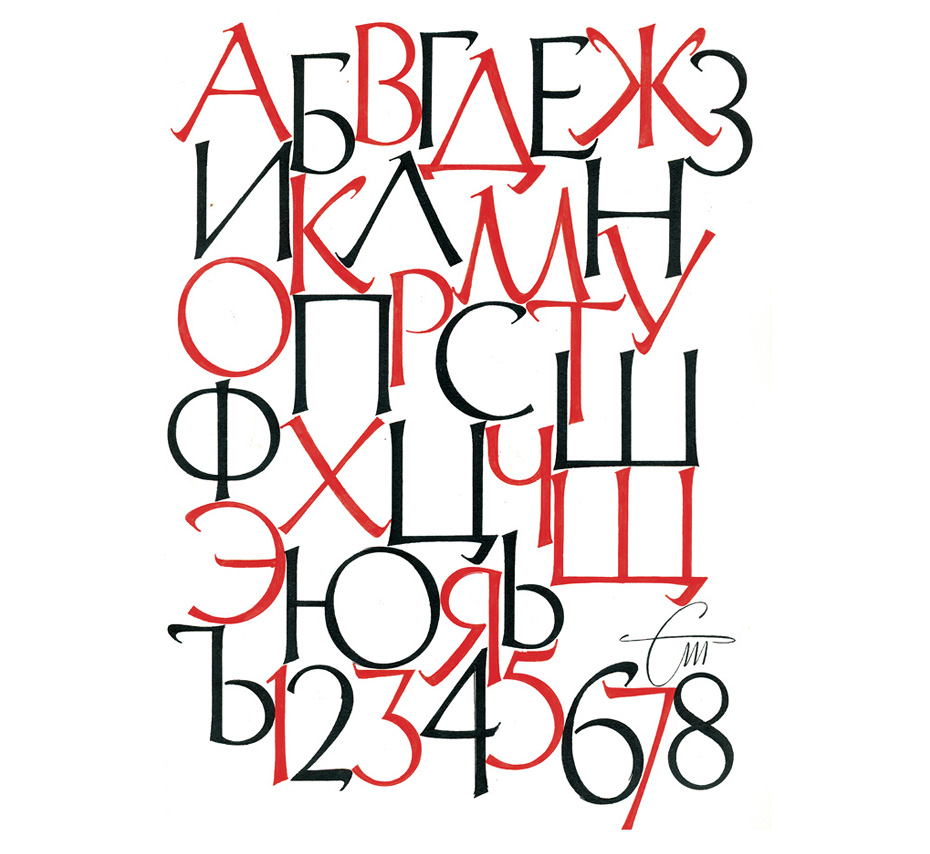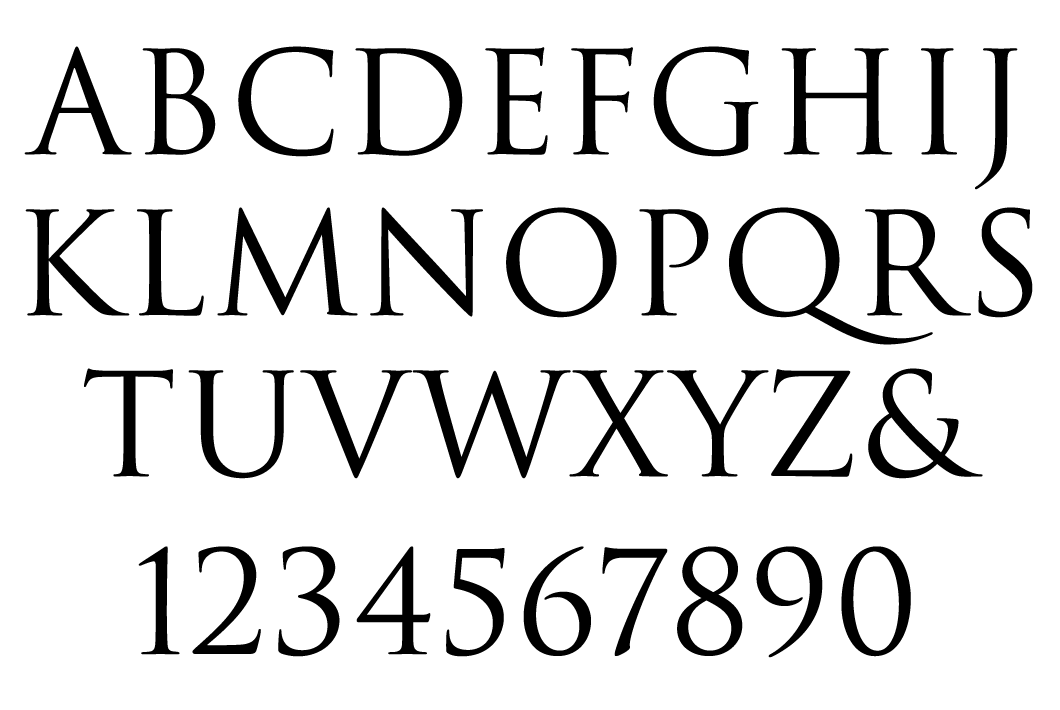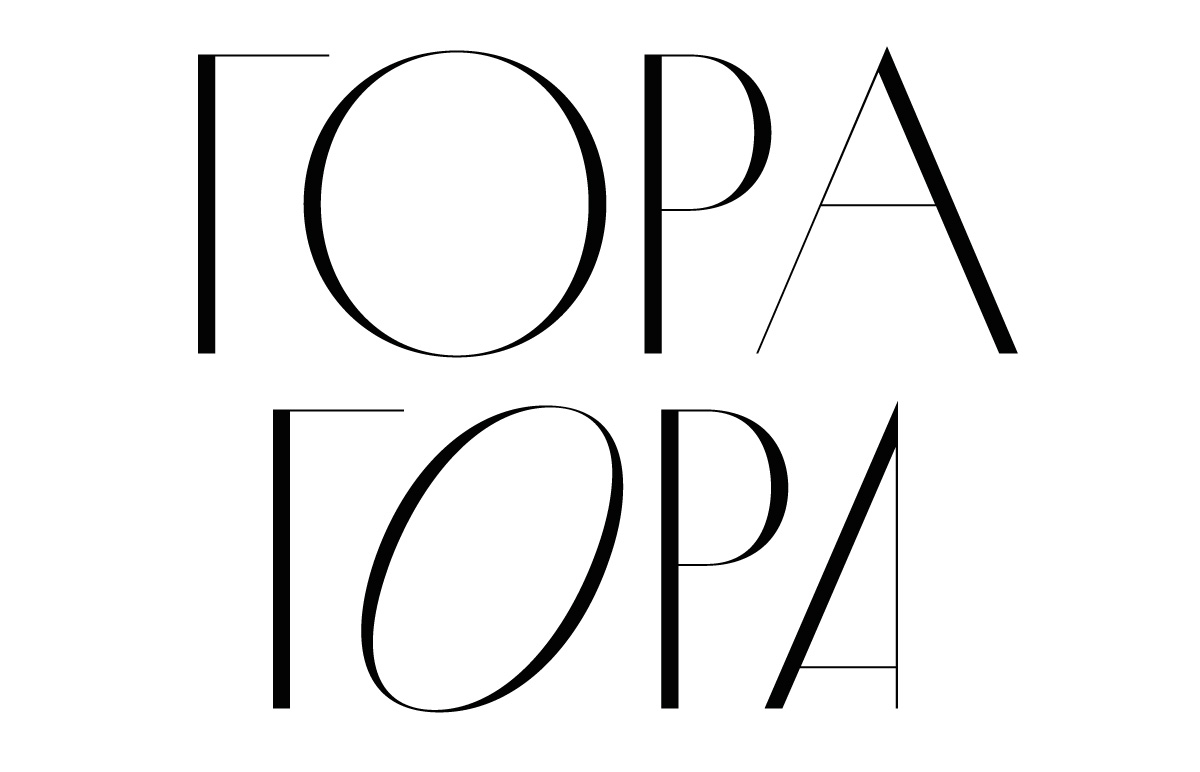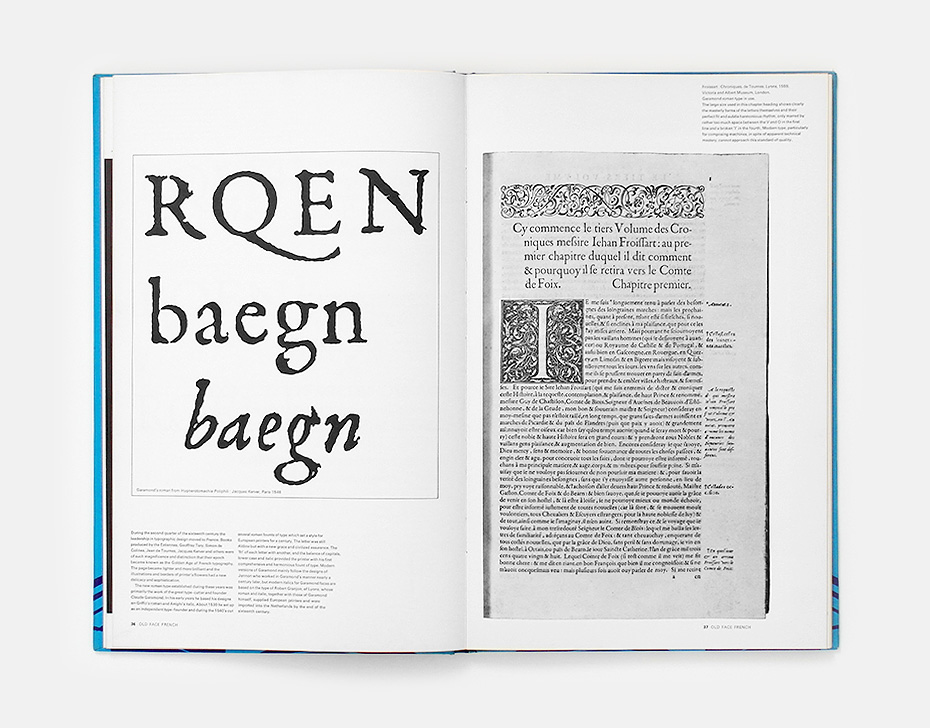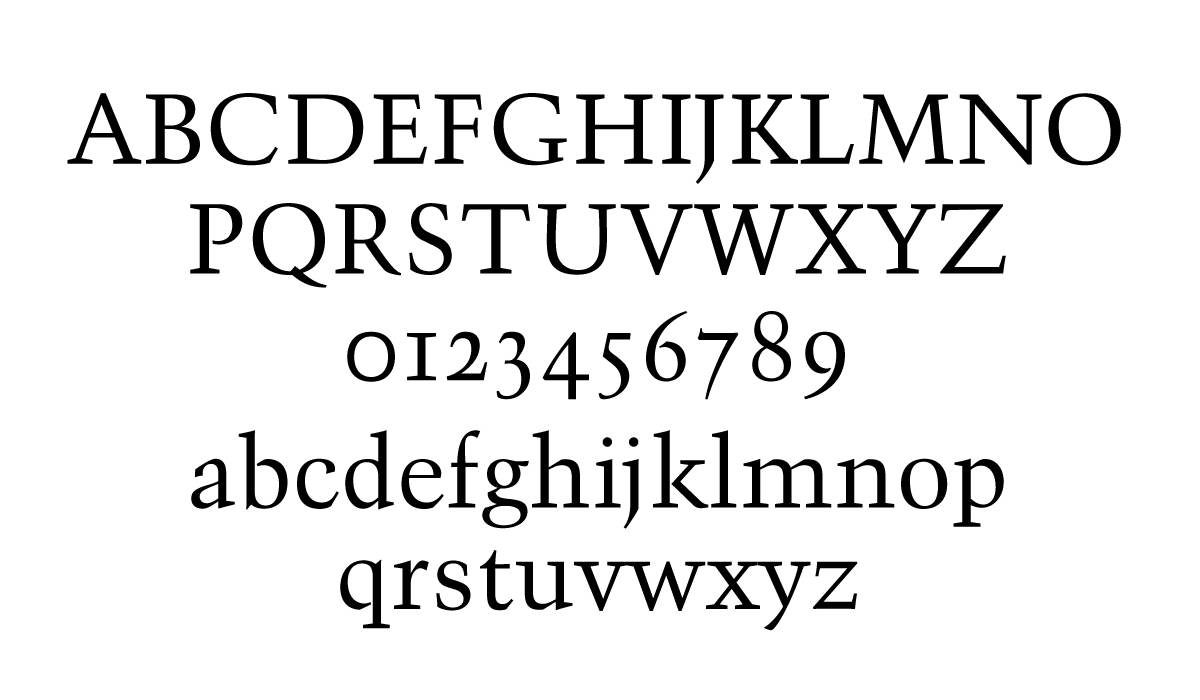
Рустам Габбасов: «Шрифт – это искусство!»
Оказавшись в арт-резиденции Переделкино в буквальном смысле слова за одним столом с Рустамом Габбасовым, сооснователем специализированного онлайнового журнала «Шрифт» и сопутствующего ему издательства Sсhrift Publishers, я не мог упустить возможность поговорить с ним о его любимом деле.
Потому что шрифтовики – совершенно отдельные люди, вызывающие восхищение у и филологов, и у дизайнеров: то, чем они занимаются, ускользает от рационального понимания – но хорошо чувствуется на подсознательном уровне.
Мой первый вопрос – о том, когда и почему возникло это издательство, столь узко специализированное?
Рустам Габбасов: Оно возникло осенью 2013 года по очень простой причине. Мне и моему другу и соиздателю Евгению Юкечеву очень не хватало ресурса, на котором бы регулярно появлялись профессиональные тексты об истории шрифта, о типографике, о книжном дизайне. Мы оба были в тот момент выпускниками Британской школы дизайна, отучились на курсе у Ильи Рудермана, основателя шрифтовой студии CSTM Fonts (совместно с Юрием Остроменцким) и шрифтового магазина type.today. И вот в 2013 году мы запустили онлайн-журнал под названием «Шрифт» (typejournal.
ru), пригласили к участию редколлегию. Нам очень важно было, чтобы у нас был экспертный состав коллег, с которыми мы могли бы сверять наши планы.
С кем же?
Рустам Габбасов: Юрий Гордон, Валерий Голыженков, Дима Барбанель, Евгений Григорьев, Гаянэ Багдасарян, Владимир Кричевский, Илья Рудерман и Эмиль Якупов. Это был замечательный профессиональный состав редколлегии. Мы задумали сайт не как какой-то бодрый медиаресурс, где каждый день что-то будет появляться. Скорее как ресурс, который говорит неспешным языком с внимательным читателем. Тем читателем, который хочет читать лонгриды, очень качественно проиллюстрированные, чистые с точки зрения прав. Это принципиальный момент. Тогда (да и сейчас) шрифтовой рынок сильно страдал от пиратства, и нам хотелось обратить внимание читателей на правовые вопросы.
Прежде чем мы перейдём к истории со шрифтами, ещё пару слов об истории с вашим сайтом.
Я так понимаю, это история абсолютно некоммерческая. Вы не ставили себе цели зарабатывать…
Рустам Габбасов: Зарабатывать – нет, конечно.
А как же?
Рустам Габбасов: У проекта несколько учредителей, вернее, партнёров. Все они оказали финансовую либо техническую помощь. Во-первых, в 2013 году это была компания «Яндекс», которая с энтузиазмом идею такого журнала восприняла. Дима Барбанель вместе с «Яндексом» создавал тогда Сampus, регулярные интенсивы для дизайнеров в Подмосковье. Женя при поддержке Мастерской Димы Барбанеля представил проект журнала «Яндексу». Так у нас появился хороший бюджет, который нам позволил запуститься.
То есть вам просто выделили бюджет. А по какому департаменту его провели? По пиару, по разработкам?
Рустам Габбасов: Нет, по коммуникациям, если не ошибаюсь. Департамент дизайна тогда в «Яндексе» возглавляла Лола Кристаллинская.
Бюджет позволял нам поддерживать финансово наших авторов, наследников художников — мы старались держать планку гонораров на достойном уровне и даже гордились этим.
Да уж, действительно, повод для законной гордости!
Рустам Габбасов: Для нас это была принципиальная установка. Ещё одним партнёром была компания «ПараТайп», которая и сегодня нас поддерживает – это известнейшая в России студия, выпускающая шрифты с кириллицей, и лично Эмиль Якупов – на тот момент директор компании. Его энергия и блестящая эрудиция нам помогли найти опорные точки в работе. Так с финансовой и дружеской помощью партнёров мы и запустились – с негласным условием, что никто не вмешиваeтся в редакционную политику. Мы, естественно, не должны были как-то подспудно рекламировать ни «Яндекс», ни «ПараТайп» – это была меценатская, просветительская история с их стороны.
И как же вы перешли от издания сайта на деньги просвещённых спонсоров к изданию книг? Конечно, история естественная, что люди, озабоченные шрифтами, хотят видеть свои шрифты на бумаге.
Но как это практически осуществилось?
Рустам Габбасов: В 2013 году прошла первая международная шрифтовая конференция «Серебро набора»…
Какое название!
Рустам Габбасов: «Серебро набора» – это несколько снобистский термин, которым типографы-классики называют идеально ровный блок текста, однородный по цвету отпечатка набор: красивый, чёткий, без просветов и дырок. По одной из версий, он возник в эпоху голландских издателей Эльзевиров, их безупречно набранные и отпечатанные книги восхищали современников. И к этой конференции (а мы там рассказывали про журнал) нам хотелось что-то выпустить, что можно подарить, продать, показать. Это была небольшая брошюра, которую мы подготовили на основе нашей первой публикации в журнале. Она называлась «Гражданский шрифт и кириллический Киш».
КиШ?!
Рустам Габбасов: Киш. Сейчас поясню. Автором этого очерка был Владимир Венедиктович Ефимов – художник, график, арт-директор компании «ПараТайп».
Это его рассказ о том, как он cпроектировал кириллический состав знаков в гарнитуре, которая называется Kиш (Kis) – по имени художника и пуансониста Николая Киша (Tótfalusi Kis Miklós, 1650–1702). Он венгр по происхождению, уникальнейшая личность – не будучи ни художником, ни гравёром, а будучи, в общем, человеком слова, философом и теологом, он оказался откомандирован в Амстердам для того, чтобы изучить ремесло типографа и шрифтовика и на венгерском языке издать Библию. Он отправился в Амстердам и не только научился у голландцев ремеслу типографа и издателя – он их во многом превзошёл. И оставил после себя приличное количество шрифтов, образцы которых сохранились во многих европейских странах. И вот антикву Kis, которая в цифровом виде уже существовала в компании Bitstream, Владимир Ефимов и кириллизовал. Это был интереснейший процесс, где он рассказывает ещё и очень кратко об истории гражданского шрифта.
У него была идея, что если бы Пётр не торопился, а посмотрел вокруг и обратился к каким-то ярким образцам антиквы того времени, то кириллица послереформенная могла бы выглядеть немножко иначе.
А одним из лучших образцов как раз были шрифты Николая Киша. Мало того, у Петра на уровне двух рукопожатий был доступ к этому человеку – просто не сложилось. Русские послы знали о Николаусе Кише, и если бы Пётр с ним познакомился, это был бы несколько иной дизайн-процесс, говоря современным языком.
Но ведь венгерский алфавит пишется латиницей. Там есть всякая диакритика, но на основе латиницы. А были к тому времени гражданские, не церковные кириллические шрифты – в Болгарии, в Сербии? Или Пётр был первым, кто заказал светским шрифтовикам кириллицу?
Рустам Габбасов: Пётр был первым, кто, что называется, примерил гражданское платье на полуустав. Он очень хотел латинизировать саму графику. И, конечно, это был абсолютно прорывной проект. Можно вспомнить разве что Людовика XIV. У него был похожий проект. Он не занимался, естественно, изменением графики алфавита, но он создал, по сути, государственный шрифт – так называемую королевскую антикву.
Это был очень серьёзный проект с комиссией из художников и гравёров, которые спроектировали romaine de roi, королевскую антикву, ей набирались самые торжественные и важные документы, книги в том числe, например, сборник, посвящённый всем наградам и медалям эпохи Людовика.
Я понимаю, что вы сели на своего конька. Но давайте вернемся от Людовика к вам. Итак, вы выпустили эту брошюру к конференции и поняли, что это хорошо.
Рустам Габбасов: И мы поняли, что наш журнал, на котором уже появилось какое-то количество публикаций, – это хороший источник для новых книг. И с 2014 года параллельно запустили издательство. Изначально мы думали, что это будет коллекционная история: брошюры, которые люди будут собирать, подшивать. Но от этой идеи мы быстро ушли.
И к чему же пришли?
Рустам Габбасов: Мы пришли к тому, что нам интересно делать хорошие большие монографии, ресурсом для которых могут быть частные архивы, коллекционеры и те исследования, которые мы параллельно готовим для журнала.
И, конечно, переводные книжки, потому что всё-таки западный типографический мир немыслим без большого количества очень качественных и хороших, интересных книг по шрифтам, чего у нас, в общем, почти и не было в тот момент.
Сколько вы книг выпускаете в год?
Рустам Габбасов: Если мы две книги в год издаём, мы считаем, что это хороший результат.
А вот когда вы говорите «мы», какое количество работающих людей имеется в виду?
Рустам Габбасов: В редакции восемь человек. Я работаю выпускающим редактором, Женя Юкечев — наш главред, я в Москве, Женя живёт в Берлине с семьёй. С нами также Олеся Гиевская, наш редактор и друг всех авторов, сейчас она живёт и работает на Кипре. Наташа Гареева — литературный редактор и корректор, Настя Минасова, исследователь, а также Владимир Пушкарёв, Науэль Бенку, Светлана Виноградова.
Последних трёх мы пригласили в редакцию в качестве интернов около года назад, и сейчас они они нам помогают с развитием соцсетей, вёрсткой новых статей в журнале, фотосъёмкой, редактурой… Вот такая разбросанная по миру, но дружная редакция, у всех есть другая работа, а «Шрифт» — это проект, которому каждый из нас посвящает свободное время по мере сил и вдохновения.
Но в экономическом или хотя бы символическом смысле оно себя оправдывает?
Рустам Габбасов: В этом году у нас есть цель — заново переделать наш интернет-магазин (им занимается как раз Володя Пушкарёв), скорректировать ритм постов в соцсетях и рассылку, проверить — позволит ли он окупать затраты на вышедшие книги, а ещё лучше — собирать бюджет на новые издания. Это будет хорошим результатом в нынешнее время.
У вас очень узкая целевая аудитория, но она очень лояльная.
Рустам Габбасов: Очень! Про нашу аудиторию хочется петь какие-то арии, петь ей дифирамбы.
Потому что это самые терпеливые люди в мире. После того, как «Яндекс» нас покинул, мы стали издавать книги по модели краудфандинга на сайте planeta.ru. Вот эти две условные книжки в год – это, как правило, краудфандинг.
То есть вы сначала собираете заказы…
Рустам Габбасов: Пока мы делаем книжку, идут предзаказы, и после того, как книжка из типографии приезжает, мы треть тиража сразу рассылаем…
А какие у вас тиражи?
Рустам Габбасов: 500 и 1000. Последние книжки мы тысячным тиражом делали, и этого нам хватает, чтобы ещё понемногу остаток тиража распродавать. Так вот, читатели, которые участвуют в краудфандинге, готовы ждать эту книгу иногда больше, чем полгода после того, как мы получили тираж, потому что нам нужно ещё спланировать рассылку, собрать «акции», которые есть всегда в краудфандинге. В общем, это всегда технически непростая история, и мы, несмотря на все наши промахи, откровенные косяки и недоработки, практически никогда не получали от наших подписчиков каких-то нареканий.
Ну а тиражи-то эти расходятся?
Рустам Габбасов: Расходятся, но небыстро. Некоторые быстрее. У нас есть такой термин внутри издательства – «фестивальные книги». Это книги, про которые мы заранее знаем, что они будут хорошо расходиться. Такой книжкой был наш «Путеводитель по кириллице», в котором мы собрали все наши рейтинговые публикации. Мы каждый год в журнале публикуем что-то вроде топа «10 самых интересных шрифтов с кириллицей». Эти публикации популярны – мы по статистике посещений видим. Всё-таки люди любят рейтинги, хотя эти публикации не про раздачу медалей — они скорее про экспертный, любопытствующий взгляд на прошедший шрифтовой год. В результате после пяти лет публикаций таких рейтингов мы собрали из них книгу. То есть одновременно это великолепные образцы шрифтов на бумаге – можно держать книгу на полочке, можно посмотреть на них, шрифты свёрстаны в разных ситуациях типографических – от суперкрупного кегля до очень мелкого. И плюс мы добавили в эту книгу (чтобы это не был просто альбом шрифтов), два хороших исследования. Одно из них написал Евгений Юкечев – это краткий экскурс в историю кириллицы, от самых первых её этапов появления и развития через все кульбиты к современности. И второе исследование написали наши друзья, каллиграфы, дизайнеры Ира Смирнова и Макс Ильинов. Оно скорее философское и посвящено тому, какие сейчас есть пути развития кириллической графики: чем могут люди вдохновляться, где спрятаны источники вдохновения.
Евгений Юкечев 2021 Фото: Екатерина Чащина/ журнал «Шрифт»
Как раз по поводу путей развития шрифтовой графики хотел у вас спросить: пришествие компьютеров, которые стали персональными, но при этом унифицированы – у всех или семейство вшитых предустановленных шрифтов виндоусовских, или, соответственно, эппловских – это облегчает задачу дизайнера-типографа – у всех всё одинаково! – или, наоборот, усложняет ее?
Рустам Габбасов: Если честно, то для профессионального типографа это не так уж важно – то, что сейчас у всех пользователей на всех компьютерах одни и те же шрифты установлены. Потому что всё-таки профессиональный типограф обращается не столько к простым юзерам, которые используют Microsoft Word для набора своих текстов, а всё-таки к коллегам-дизайнерам. А коллеги-то прекрасно знают, что шрифтовой мир гораздо шире, чем те стандартные шрифты, которые установлены в компьютер. И в этом смысле компьютерный шрифтовой дизайн, конечно, открыл огромные возможности для графиков. Это был прорыв – стало возможно у себя дома, за рабочим столом, не просто рисовать, проектировать новые шрифты, но и тут же ими пользоваться, не обращаясь ни в типографии, ни в сторонние печатные дома. Исчезла морока с плёнками, которые нужно выводить, проверять и прочее, прочее. Всё очень ускорилось, произошло даже перенасыщение новыми шрифтами. Но у нас, в отличие от Запада, ситуация немного иная – у нас до этого перенасыщения пока ещё далеко. Как только появляется какой-то новый оригинальный качественный шрифт с кириллицей, профессиональное сообщество дизайнеров мгновенно вбирает его в себя, осваивает, он появляется на улицах, в книжках, в журналах и так далее.
Это вы так деликатно говорите о нелицензионном использовании?
Рустам Габбасов: Нет. В том-то и дело, что сейчас всё больше и больше шрифты используются легально. В этом смысле рынок шрифтовой немного подправился. Ушла та эпоха, когда шрифты продавались на дисках на Горбушке. Сейчас пользователи относятся к шрифту как к вещи коллекционной, как к вещи, которая у тебя будет храниться долго на компьютере (имеется в виду лицензия), и ты сможешь пользоваться ей снова и снова, то есть как к некому вложению средств.
А есть ли вообще при разработке новых шрифтов какая-то мера? Когда модификация известного шрифта становится новым самостоятельным шрифтом? Если я добавлю к засечкам с каждой стороны по два пикселя, это будет новый шрифт? Как вообще это определяется?
Рустам Габбасов: Конечно, можно взять какой-то готовый шрифт и чуть-чуть что-то в нём поменять, и это даже может не стать прецедентом в суде. Но это бессмысленная работа. Поиск нового образа в шрифте абсолютно такой же, как поиск нового образа в живописи, в литературном произведении – в любой творческой работе, потому что шрифт – это искусство.
Там есть свои законы, по которым ты добиваешься, доползаешь до нового ощущения от шрифта. У шрифтов, которые, казалось бы, даже очень похожи на уже существующие, есть невероятное влияние на читателя. Оно достигается за счёт изменения параметров не столько микротипографических – не в засечках дело, — а макротипографических, например, в отношении высоты строчного знака к высоте прописного, в изменении контраста внутри знаков, то есть перепаде толщин – как самый тонкий штрих относится к самому толстому. От таких нюансов меняется динамика чтения, восприятие текста.
Вот на таком макроуровне профессиональный шрифтовой дизайнер и работает – как диджей, передвигающий ручки на микшере. Он взаимодействует с существующими историческими стилями и эпохами, но, чтобы сделать шрифт новым и современным, чуть меняет эти настройки. Так появляются новые оригинальные шрифты. Сегодня есть большие возможности технологические, связанные с программированием, не только с рисованием. Ведь шрифтовое семейство можно задумать как гарнитуру из двух шрифтов – прямое и наклонное, например, а можно – из сорока: ты нарисовал самое светлое, самое жирное, а остальное за тебя делает компьютер, интерполирует все градации, и ты из них можешь выбрать то, что тебе нужно. Такое подключение к творческому технологического процесса – это тоже интересно.
Включаются ли в современные гарнитуры эмотиконы? Или, проще сказать, эмоджи? Потому что людям, которым сейчас меньше 20 лет, уже неудобно переписываться без эмотиконов. Это стало частью стандартной переписки.
Рустам Габбасов: Эмотиконы встроены в операционные системы, и ты быстро к ним можешь добраться. А шрифт подключить, например, в тот же айфон и заменить им те эмотиконы, которые там есть, это уже непросто. Но есть, во-первых, очень давняя традиция шрифтов из неалфавитных знаков. Например, шрифтов, в которых есть только знаки зодиака или фазы луны. Это очень давняя традиция, которая идёт ещё из эпохи металлического набора, и сегодня дизайнеры, рисуя даже текстовый шрифт, всегда добавляют туда огромное количество символьных элементов – стрелки или «персты указующие».
Дизайнеры любят отрываться именно на этих элементах – там можно порисовать эти руки, они смешные.
«Персты указующие» – это здорово, но я говорю о детях, которые сейчас растут на смартфонах, где эти самые эмотиконы, эмоджи встроены уже в обычный текст. Им дальше уже некомфортно будет без этих рожиц в обычной своей взрослой и профессиональной жизни общаться. Вы это предвидите как-то?
Рустам Габбасов: Я всё-таки не верю, что возможно обойтись, во-первых, без начертания рукой всех алфавитных знаков, без письма, и, во-вторых, без шрифта, где есть знаки, которые можно читать. Ведь это явления, которые буквально сидят в нашем ДНК.
В нашем, но не наших детей.
Рустам Габбасов: Там просто произойдут какие-то гибридные процессы. Потому что на одних только эмодзи невозможно научиться читать. Понятное дело, что будут, и уже есть книжки, где история рассказана только какими-то эмодзи, но все нейронные связи у нас отомрут, если мы лишимся привычного алфавита. Невозможно научиться мыслить, не записывая что-то рукой сначала, а потом не взаимодействуя с печатным текстом.
Тогда позвольте вам предложить еще более глобальный вопрос. Есть западноевропейский алфавит, который одинаков от Швеции до Италии. Да, есть диакритика, какие-то дополнительные значки, но любое слово шведского языка можно узнаваемо записать на итальянской пишущей машинке, и наоборот. Есть языки и алфавиты, заведомо ничего общего не имеющие с западноевропейским: грузинский, армянский. Это совершенно отдельные знаковые системы. А наша с вами родная кириллица как бы занимает промежуточное положение – вроде как большинство знаков у нее совпадает с европейскими, но в слова эти знаки, с точки зрения европейца, всё-таки не складываются.
Рустам Габбасов: Да, можно так сказать.
Вы, кириллические шрифтовые дизайнеры, в европейском семействе шрифтовиков кем себя чувствуете? Бедными родственниками или, наоборот, обладателями суперспосбности – вы и так, и эдак можете?
Рустам Габбасов: Нет, такой суперспособности, к сожалению, нету. Но по поводу ощущения «бедных родственников» по сравнению с латиницей – это очень интересный разговор. С момента перестройки, когда в стране появились первые компьютеры, стали появляться первые шрифты с кириллицей, часто у кириллических дизайнеров было снобистское отношение к западным шрифтовым дизайнерам – мол, они никогда не смогут нарисовать качественную кириллицу.
Оно им надо?!
Рустам Габбасов: Оно им нужно было, потому что, когда появились компьютеры с «Виндоус», мы получили огромное количество системных шрифтов с некачественной кириллицей. Люди, их рисующие, просто не воспринимали кириллицу как какой-то алфавит, которому нужно уделить внимание. Допустим, сотню языков поддерживает шрифт Times New Roman, и кириллица – просто ещё один алфавит, зачем же к нему как-то особенно относиться?
Сотня языков – это не сотня алфавитов. Едва ли Times New Roman поддерживает сотню алфавитов.
Рустам Габбасов: Он поддерживает, конечно же, не сотню алфавитов, но всё-таки к проекту приглашались серьёзные консультанты, которые, во-первых, владеют тем или иным языком и знают, как выглядит графика их алфавита. А с кириллицей такого не происходило. Мы получили ужасный шрифт Arial, который сам по себе отличнейший проект в латинице, но в кириллице он просто-напросто страшный. И у нас он был повсеместно на всех вывесках.
Но за последние годы произошла благостная глобализация, я бы сказал. Западные шрифтовые дизайнеры без стеснения обращаются к молодым ребятам у нас в России, которые рисуют шрифты, за консультацией. Это отдельный жанр работы шрифтового дизайнера кириллического, – консультации, потому что это особое умение – объяснить коллеге с Запада, где что-то неправильно нарисовал или нарисовал правильно, но ошибся с пропорцией буквально на пару пунктов – и в строке это сразу видно.
И эта история сейчас продолжается. Люди, которые самостоятельно рисуют кириллицу на Западе, стали делать гораздо меньше ошибок. И, например, в пакете шрифтов от компании Adobe уже есть гарнитуры, которые нарисованы без привлечения наших дизайнеров в качестве консультантов, но они выглядят очень хорошо – ими можно набрать серьёзную книжку, длинный текст. И вот это процесс, в котором мы (редакция журнала) себя видим тоже как некий катализатор, что ли. И с помощью журнала и отчасти при помощи наших книг эту довольно маргинальную идею о кириллице – «это только наше, и только мы можем это сделать», мы за последние 10 лет подразрушили. Пожалуй, мы сделали шрифты и типографику актуальной, даже модной темой – и сообщество дизайнеров, которое нас читает, видит, насколько это интересная, экспертная тема. Я рад, что мы смогли для довольно широкой аудитории рассказать о наших коллегах, о наших друзьях, о молодых дизайнерах, которые, отучившись в разных вузах, продолжают рисовать шрифты.
А общаетесь ли вы как-то более тесно с нашими, можно сказать, братьями по кириллице – болгарами, сербами, украинцами, белорусами, македонцами? Может быть, заказываете им статьи, книги?
Рустам Габбасов: Это интересная тема. У нас есть замечательные авторы, которые живут в Украине. Например, Константин Головченко – блестящий исследователь, он написал для нас несколько статей. Но статьи именно об особенностях графики украинского алфавита ещё ждут своего часа. Там есть свои особенности. В «Путеводителе по кириллице» мы их частично показали, нужно продолжать. С болгарами интересно – их кириллица похожа на нашу, но они отстаивают, например, непривычные нам выносные элементы. Или рукописные формы строчных «д», «з», «в». И у них таких микросдвигов в графике алфавита довольно много, причём она тоже не очень устоявшаяся, как и в нашем случае.
«Болгарица» рядом; а надо ли нам всем учить китайский? То есть, займёт ли иероглифическое письмо то место, которое сейчас в нашем мире занимает латинский алфавит? И что будете делать вы, шрифтовики?
Рустам Габбасов: Не думаю, что в ближайшее время это произойдет. Всё-таки это отдельная вселенная, про которую мы почти ничего не знаем и ничего не понимаем, как это устроено и с точки зрения графики, и смыслов. И поэтому, кстати, специалисты по иероглифам на вес золота.
Напоследок вернёмся от глобального к конкретному. Какие ваши ближайшие пара книг?
Рустам Габбасов: Из ближайших – та, которой занимаюсь здесь в резиденции, она называется «Modern Typography» («Современная типографика»), эссе английского типографа Робина Кинросса. Это краткая, ёмкая, и полная спорных мыслей история типографики и, самое главное, попытка разобраться, что такое понятие современности в типографике, в типографическом мире. С какого момента типографика стала себя осмыслять как самостоятельную дисциплину и искусство. И в этом году мы переиздадим нескольких наших книг. Статья Владимира Фаворского «О шрифте» выйдет в третьем издании. Эту книгу мы делаем вместе с внуком художника Иваном Дмитриевичем Шаховским. И у нас есть в планах работа над ещё одной переводной книгой, но уже с января следующего года. Эта книга называется «While we are reading» – «Как мы читаем». Автор – голландский типограф Герард Унгер, который, к сожалению, в прошлом году умер.
И у нас есть огромное количество, что называется, неизученных архивов. Архивы наследников художников, или, например, архив НИИ Полиграфмаш – в советское время была такая организация, которая занималась разработкой новых шрифтов и обслуживанием, скажем так, языков советских республик. От этого архива мало что уцелело, но то, что сохранилось (а это кальки, эскизы, это стеклянные пластинки, отчёты художников об их работе), нас очень интересуют. Мы пока не понимаем до конца, как всё это наследие превратить в книгу. Наверное, надо начать со статей, а потом уже перейти к книжке.
Новые шрифты в инстаграме: что говорит о нас наш выбор
Август стал важным месяцем для Instagram. Сначала социальная сеть выпустила довольно несуразную копию TikTok — Reels, которую сразу же встретили негативными отзывами. Еще одним нововведением стали четыре новых шрифта, которые Instagram сделал доступными для широкого использования в Stories. И вот это действительно стало событием. Да, мир переживает пандемию, вот-вот начнутся самые важные выборы в современной Америке, а в обществе царит глубокая социальная нестабильность. В этой парадигме шрифты, конечно, не самая насущная проблема, хоть как-то влияющая на нашу жизнь. Тем не менее мы решили рискнуть и проанализировать, что говорит о нас наш повседневный выбор в социальных сетях.
Мы все знаем, что выбор шрифта может многое сказать о человеке. Times New Roman и Calibri — это, как правило, соперничающие друг с другом студенческие группки на парах английского; и ничто не выдает в вас строгой чопорности больше, чем Century Gothic в качестве стандартного шрифта для электронной почты. Новые шрифты Instagram варьируются от обычных до тонких и выхолощенных, словно позаимствованных у сайта The Cut. Инстаграм не дал нам названий новых шрифтов, поэтому мы взяли смелость сделать это сами. Мы также смоделировали подходящие к ним ситуации. А потом присвоили каждому из них индивидуальность, чтобы вам было проще понять, к чему больше лежит душа. Что говорят новые шрифты о том, какой вы человек? Что подходит именно вам и вашей стратегически выверенной виртуальной личности?
Normal (стандартный шрифт) LAUREN KRANC«Я просто классная сама по себе и не задумываюсь слишком о таких мелочах»
Этот пользователь либо не подозревает, что шрифты можно менять, либо делает намеренный стилистический выбор, чтобы показать: он даже не старается и не воспринимает свои сторис в Instagram слишком серьезно. Вы похожи на тех, кто отдает предпочтение шрифту «пишущая машинка», однако более разумны. Normal — скучно, зато стабильно.
Thin Caps LAUREN KRANC«Кто еще сегодня идет на Дэйва Мэттьюза?» (южноафриканский и американский музыкант и актер. — Esquire)
Любители этого шрифта стоят прямо перед дверями метро, а не проходят к середине поезда. Они до сих пор носят свой браслет с фестиваля «Боннару» 2017 года, и у них есть уже заготовленный монолог на случай, если кто-либо сообщит, что распутавшаяся часть шнурка на браслете — рассадник бактерий. Они предпочитают янтарный эль и ведут долгие разговоры с соседями по столикам, пока их друзья не решат перестать приглашать их на ужин.
Fancy Cursive («красивый курсив») LAUREN KRANC«Розе весь день»
Любители курсива живут в очень специфическом, придуманном мире. Эти люди с легкостью могут просто не видеть всего плохого, что сейчас происходит. Они ходят на чаепития с мамой. Они делают сторис с фотоколлажами, поздравляя каждого из своих старых добрых друзей с днем рождения. Они подбирают губную помаду под цвет лака для ногтей и следят за цветовой палитрой книжных полок у себя дома.
Almost published («почти издан») JUSTIN KIRKLAND«Мир открыт ровно настолько, насколько тебе открыта книга с книжной полки, которую ты решишься прочитать»
Юзеры шрифта «почти опубликовано» (он же — шрифт «пишущая машинка») публикуют только микро- или макрофотографии. Они до смешного интроспективны. Если вам случится забрать у них телефон, вы обнаружите там целое множество неопубликованных стихотворений в заметках. Содержания? Совершенно непонятного. Такой человек предпочел бы простые, индустриальные интерьеры у себя дома, будь у него деньги, но стихи… Они просто не могут заставить себя их продать. Но когда-нибудь — обязательно. Это тот человек, который обязательно спросит на свидании, знаете ли вы что-то об А24. Ну, знаете, такая киностудия?
Bro (бро) LAUREN KRANC«Работай усердно, играй усерднее»
Использовать шрифт Bro — значит предпочитать ясность и простоту, а еще иметь кучу шмоток от Nike. Это хайпбист среди шрифтов. Его юзерам нравятся кроссовки, даже если они сами отдалены от культуры сникерхедов. Слишком токсично, чувак. Любители этого шрифта используют его для публикации своих велосипедных маршрутов Strava в сторис, потому что действительно гордятся своими 20 милями в час. Никто, кроме велосипедного сообщества, на самом деле не знает, что это значит.
Comic Sans Adjacent (что-то похожее на Comic Sans) JUSTIN KIRKLAND«Не о чем беспокоиться по поводу…»
Этот шрифт — абсолютный хаос, но привлекательным его делает тот факт, что хаос может принимать разные формы. В самом невинном виде использование Comic Sans в Instagram — тот шаг, на который пойдет мама чуть за 40. У нее безумная «я должна выбраться из этого продуктового» энергия. С другой стороны шрифтового спектра, Comic Sans может означать, что перед вами психопат. Вы когда-нибудь смотрели фильм, где оживала кукла, и была та доля секунда, когда она уже ожила, но еще никого не убивает? Вот это и есть энергия Comic Sans. Атмосфера, которую его пользователи передают всем своим читателям.
The Cut (что-то похожее на шрифт The Cut) JUSTIN KIRKLAND«Почему я еще не получил ответа на свое резюме?»
Использовать этот шрифт — то же самое, что носить красную поясную сумку Gucci в 2020-м. Люди, использующие его, вероятно, недоумевают, почему The Cut не ответил ни на одно из их восьми резюме, которые они отправили по почте прямиком главному редактору. Они никогда не публикуют фотографии в инстаграме с синим фоном, ведь их лента равномерно бледно-розовая, и это испортило бы общую эстетику. Они часто мониторят себя в интернете. Сейчас они делают ремонт в квартире, декорируя ее распечатанными феминистическими картинками, ибо будущее — женское, чувак. И они не прочь занять место у стола с неоновой вывеской на заднем плане, если можно!
Android JUSTIN KIRKLAND«Фейстаймлюсь со своим лучшим другом»
У этого шрифта сильный и отчетливый вайб пользователя андроида. Это наименее перформативный из всех шрифтов — когда вы его используете, то активно пытаетесь не выкладывать слишком много. Почему тогда не Normal? Дело в том, что он предполагает, что вы уже разобрались со своей индивидуальностью, не запутываясь в странной необходимости использования засечек только для того, чтобы вас услышали. Юзер шрифта Android — добрая душа. Посредник среди друзей. Они не заботятся о соотношении читаемых и читателей. Это тот, кто готов примириться с групповым решением заказать мексиканскую еду, хотя уже тысячу раз сказал, что не любитель.
New Money Serif (шрифт «Новые деньги») JUSTIN KIRKLAND«Правильный негрони может исправить любую ситуацию»
Этот шрифт — про иллюзию богатства. Его использование предполагает роскошь, хотя юзер может ничего не знать о деньгах. У этого шрифта уже есть пенсионный счет, даже если его нет у самого пользователя. В нем есть своя простота, которая и делает его таким привлекательным. Простая засечка. Тонкая линия. Его использование говорит о том, что вы относитесь к себе серьезно, но в случае чего — будьте внимательны. Его предпочитают те, кто хочет казаться самодостаточным, но всего лишь пара хитов на концерте Chainsmokers в Хэмптонс в разгар пандемии — и они снова вернутся к шрифту BRO, выставляя себя на всеобщее обозрение.
Выбор шрифта в Instagram — долгосрочное обязательство. Не облажайтесь — использование разных шрифтов даже хуже, чем выбор в пользу Comic Sans.
Как Майкл Бейрут из Pentagram выбирает шрифт
Майкл Бейрут — всемирно известный графический дизайнер, критик, педагог, партнер в международной дизайн-студии Pentagram. Автор книги «79 коротких рассказов о дизайне» и «Now You See It и Другие рассказы о дизайне», которая вышла осенью 2017 года. Телеграф публикует перевод адаптированного отрывка из его последней книги, где Бейрут рассказывает о своем подходе к выбору шрифтов.
Статья адаптирована из отрывка книги Майкла Бейрута «Now You See It и Другие рассказы о дизайне», которую можно купить онлайн с 8-го ноября.
Источник изображения: Princeton Architectural Press
Будучи «типографически беспорядочным» в прошлом, сейчас Майкл Бейрут обладает простым методом выбора шрифтов, подробно описанным в этом эксклюзивном отрывке из его следующей книги «Now You See it и Другие рассказы о дизайне».
Первые 10 лет карьеры я работал у Массимо Виньелли, дизайнера, который славится использованием очень ограниченного количества шрифтов. Между 1980 и 1990 годами большинство моих проектов были реализованы в пяти шрифтах: Helvetica (естественно), Futura, Garamond # 3, Century Expanded и, конечно же, Bodoni.
Для Массимо это был идеологический выбор, этический императив. Однажды он написал: «В новый компьютерный век распространение шрифтов и манипуляции с ними представляют новый уровень визуального загрязнения, угрожающий нашей культуре. Выберете из тысячи шрифтов несколько нужных базовых и выбросьте остальные». Для меня это стало инструментом экономии времени. Зачем тратить часы на выбор между Bembo, Sabon и Garamond № 3 каждый раз, когда вам нужен Venetian Roman? Для большинства людей, например, для моей мамы, — это разница без различий. Почему бы просто не привязаться к Garamond № 3, чтобы никогда больше об этом не думать? Мое католическое школьное образование, должно быть, стало благодатной почвой для нравственной четкости. За это я ему благодарен.
Спустя десять лет я оставил свою первую работу. Внезапно у меня появилась возможность использовать любой понравившийся шрифт. И меня понесло. В одном из первых проектов я использовал 37 разных шрифтов на 16 страницах. Моя жена, которая сама посещала католическую школу, сказала, что ей это слишком знакомо. Она вспомнила одноклассников, которые после 8 лет монашеского обучения перешли в государственную школу. Наконец-то освободившись от скромной клетчатой формы, они носили самые короткие юбки, которые могли отыскать. «Господи», — сказала она, глядя на гонки на выживания среди многочисленных шрифтов. «Ты превратился в настоящую шлюшку, не так ли?»
Это правда. Наконец-то свободный от моногамии, я стал типографически беспорядочным. Мне кажется, с тех пор я научился модулировать свое поведение. Как любой человек, злоупотребляющий алкоголем, я понял, что запой — это трудоемко, дорого и в конечном счете непродуктивно. Но я так никогда и не вернулся к трезвости с пятью шрифтами. Эти тысячи шрифтов все там же, но реабилитация сделала меня более выборочным и заставила ответить на, казалось бы, простой вопрос: почему мы выбираем конкретный шрифт? Ниже перечислены 13 причин.
1. Потому, что он работает
Некоторые шрифты просто идеально подходят для конкретных вещей. Я определил экзотические шрифты для проектов с айдентикой, которые прекрасно работают в заголовках и даже в тексте. Но рано или поздно вам придется установить этот крошечный шрифт в нижней части карточки для делового ответа. Вот для чего создан Franklin Gothic. Но будьте аккуратны: некоторые шрифты работают слишком хорошо. Frutiger так часто использовался для вывесок в больницах и аэропортах, что теперь наводит на мысль о предстоящей диагностике опухоли головного мозга или о пропущенном рейсе до О’Хара в 19:00.
2. Потому, что вам нравится его история
Я слышал о нескольких проектах, где дизайнер нашел шрифт, который был создан в том же году, когда была основана организация клиента. Это должно создать ауру предначертанности судьбы, перед которой, естественно, невозможно устоять. Мне пока так не везло, но я до сих пор пытаюсь найти такое же гармоничное совпадение. Например, я никогда не был поклонником шрифта Eurostile от Альдо Новарезе. Но я полюбил его, работая над монографией об Ээро Сааринену: они оба разделяют экспрессивность, свойственную послевоенному оптимизму 1950-х годов.
3. Потому, что вам нравится название
Однажды я увидел проект в студенческом портфолио, в котором была предпринята сомнительная попытка редизайна айдентики для Tiffany & Co. Особенно мне не понравился используемый шрифт. Я вежливо спросил, что это. Последовал восторженный ответ: «О, это самое интересное! Шрифт называется Tiffany!»
С другой стороны, Брюс Мау разработал дизайн Spectacle, — совместной с Дэвидом Роквеллом книги — используя шрифт Rockwell. Думаю, это было забавно.
4. Из-за того, кто разработал шрифт
Однажды я работал над проектом, в котором в группу клиента входили очень сильные архитекторы. Я выбрал Cheltenham, необычный шрифт, который не только хорошо соответствовал требованиям проекта, но и был одним из немногих шрифтов, созданных архитектором Бертрамом Гудхью. Позже я разработал программу публикаций для девушек. Я использовал шрифт, разработанный одной женщиной и названный в честь другой — Mrs. Eaves от Зузаны Личко. В обоих случаях клиенты знали, что публика совершенного без понятия об истории выбора шрифта, но, тем не менее, немного успокоились. Я тоже.
5. Потому, что шрифт уже существовал в системе
Бывает, что шрифт уже живет в домике, когда вдруг появляетесь вы. Иногда решение о его выселении может выглядеть подло. «Мы используем Baskerville и Univers 65 во всех наших материалах, но можете свободно предложить альтернативные решения». Серьезно? Зачем об этом вообще беспокоиться? Это как в одном из тех шоу, где повару-аматору дают репу, пачку муки, ногу ягненка и какой-то кленовый сироп, и просят что-то из этого состряпать. Иногда вам могут попадаться шрифты, которые вы никогда не использовали ранее. Это делает процесс более увлекательным.
6. Потому, что вас заставили
Но иногда вы не используете определенный шрифт по уважительной причине. «Мы используем ITC Eras во всех наших материалах». — «Могу ли я предложить альтернативное решение?» — «Нет». В этом случае очень пригодится слепое штампование.
7. Потому, что шрифт вам что-то напомнил
Когда мне хочется, чтобы слова выглядели просто, умно и располагали к общению, я часто рассматриваю вариант Futura, в верхнем и нижнем регистре. Почему? Не потому, что Пауль Реннер был простым, разговорчивым и умным, хотя может, и был. Нет, все потому, что более 50 лет назад Хельмут Кроун решил использовать Futura в рекламе Дойла Дана Бернбаха для Volkswagen. И компания использовала этот шрифт до 2015 года. Одно предупреждение: если шрифт напоминает вам что-то, он может напоминать другому человеку что-то иное.
8. Потому, что красиво
Шрифт Сайруса Хайсмита Novia теперь доступен в продаже. Изначально он разработал его для заголовков на сайте Martha Stewart Weddings. Сопротивляться ему бесполезно. По крайней мере, мне.
9. Потому, что некрасиво
Несколько лет назад меня попросили сделать редизайн логотипа для New York Magazine. Милтон Глейзер построил оригинальный логотип на шрифте Bookman Swash Italic, который мне показался невообразимо устаревшим и уродливым. Но логотипом Глейзера заменили более ранний лого Питера Палаццо, основанный на Caslon Italic. Я предложил вернуться к Caslon и отчетливо запомнил свою фразу: «Bookman Swash Italic всегда будет выглядеть уродливым». На днях кое-что действительно привлекло мое внимание. Это был сет в Bookman Swash Italic, и он выглядел великолепно. Уродливо, но великолепно.
10. Потому, что шрифт скучный
Тибор Кальман был очарован скучными шрифтами. «Нет, этот слишком умный, этот слишком интересный», — повторял он, когда я предлагал шрифты для его монографии. По его мнению, все, кроме скучного шрифта, мешало его идеям. Мы остановились на Trade Gothic.
11. Потому, что шрифт особенный
В дизайне, как и в моде, ничто не сравнится с индивидуальным пошивом. Джонатан Хёфлер и Тобиас Фрер-Джонс, Джо Финоккиаро, Мэтью Картер и Честер Дженкинс делали мне шрифты на заказ. Потакание прихотям в высшей степени, но оно того стоит. Такой подход все усложняет? Ну и ладно.
12. Потому, что вы веруете в него
Иногда я думаю, что Массимо Виньелли, возможно, использовал слишком много шрифтов, а не слишком мало. Истинный фундаменталист требует монотеистического мировоззрения: один мир — один шрифт. Дизайнеры Experimental Jetset сделали из Helvetica целый культ. В жизни моего партнера Эбботта Миллера был период, который он называет «годы Scala». Тогда он использовал исключительно этот шрифт. Возможно, когда-то и я смогу поклясться в верности какому-то шрифту.
13. Потому, что вы не можете не выбрать этот шрифт
Когда я опубликовал свою первую книгу рассказов, то хотел, чтобы ее было приятно читать. В ней не было картинок, поэтому я попросил Эббота ее задизайнить. Он подал идею, чтобы каждый из нас предложил 79 разных шрифтов. Мне она понравилась, но я не знал, как далеко он готов зайти в этом вопросе. «Как насчет шрифта с названием «Я ненавижу ITC Garamond?», — спросил я его. «Мы бы поставили его в ITC Garamond?» Он посмотрел на меня, как на сумасшедшего. «Конечно», — сказал он. Книга, кстати, прекрасна, и ничуть не шлюховата.
Эта статья была адаптирована из книги «Now You See It и Другие рассказы о дизайне» с разрешения Майкла Бейрута (Princeton Architectural Press, 2017). Книга находится в продаже с 8 ноября. Майкл Бейрут — партнер в нью-йоркском офисе Pentagram Design.
Оригинал статьи по ссылке.
Перевод — Катя Павлевич
Зависимость восприятия текста от шрифта, которым он набран
Журнал New Scientist опубликовал краткий обзор исследований о восприятии типографских шрифтов. Поводом для публикации в New Scientist стала реакция части публики на использование шрифта Comic Sans в презентации Фабиолы Джанотти, представлявшей исследовательскую группу ATLAS, которая объявила об обнаружении бозона Хиггса в ходе работы на Большом адронном коллайдере.
Использование шрифта Comic Sans в презентации Фабиолы Джанотти, представлявшей исследовательскую группу ATLAS
У многих вызвало глубокое возмущение несоответствие шрифта и серьезного, значительного события. Среди отзывов есть и такие: «Использовать в данном случае Comic Sans – это всё равно, что прийти на похороны в гавайской рубашке». Склонные к юмору читатели предложили переименовать Comic Sans в Comic Cerns.
Эти истории показывают, что шрифт – нечто большее, чем он кажется на первый взгляд. Шрифт оказывается способным оказывать влияние на читательское восприятие и оценку текста, написанного этим шрифтом. Еще в 1955 году Сирил Бёрт и коллеги в Лондоне определяли, насколько быстро дети читают тексты с различными шрифтами. Как оказалось, даже очень похожие шрифты порой сильно различаются по степени легкости чтения. Так, Bodoni читать труднее, чем Times New Roman.
Менее очевидны результаты другого исследования, определявшего влияние шрифта на запоминание текста. В 2010 году такой эксперимент провела группа исследователей под руководством Дэнни Оппенгеймера в Принстонском университете. Они предлагали участникам запомнить 21 характеристику трех видов фантастических инопланетян. Обнаружилось, что те, кому доставался список, напечатанный более сложным шрифтом, тратили больше времени на чтение, однако запоминали куда больше деталей, чем те, кто читал список, напечатанный шрифтом Times New Roman. Позднее Оппенгеймер обнаружил тот же эффект у школьников, усваивающих учебные материалы.
Психологи Хён Чин Сон и Норберт Шварц из Мичиганского университета выяснили, что шрифт может влиять и на оценку читателем собственных возможностей.
В 2008 году психологи Хён Чин Сон и Норберт Шварц из Мичиганского университета выяснили, что шрифт может влиять и на оценку читателем собственных возможностей. Они предлагали испытуемым описание физического упражнения, напечатанное популярным шрифтом Arial или более сложным для чтения шрифтом Brush Script. После чтения участников просили оценить ложность упражнения и время, которое займет его выполнение. Те, кому доставался текст с Brush Script давали более высокие оценки сложности и времени. Эти же исследователи провели аналогичный опыт с кулинарным рецептом, отпечатанным шрифтом Arial и шрифтом Mistral, который имитирует рукописный текст. В результате те, кто читал рецепт, написанный шрифтом Mistral, считали, что блюдо будет готовиться дольше и требует более высокого уровня мастерства, чем те, кому достался Arial.
Изучалось и влияние шрифта на явление, которое в когнитивной психологии называют предвзятостью подтверждения (confirmation bias) – склонность искать в новой информации подтверждения уже имеющегося у индивидуума мнения.
Изучалось и влияние шрифта на явление, которое в когнитивной психологии называют предвзятостью подтверждения (confirmation bias) – склонность искать в новой информации подтверждения уже имеющегося у индивидуума мнения
Психолог Джесси Ли Престон из Иллинойского университета в Урбане-Шампейне предлагал испытуемым, причислявшим себя к либералам или к консерваторам, текст, содержавший аргументы в пользу смертной казни. Те, кто получал этот текст в более простом шрифте, куда чаще воспринимали эти аргументы лишь как подтверждение собственных воззрений, те же, кто получал сложный для восприятия шрифт, более взвешенно их оценивали и лучше осознавали сложность аргументов.
Во втором эксперименте участники читали документы вымышленного судебного процесса. Оказалось, что, если тексты были в более трудном шрифте, читающие могли более эффективно отсеять содержащуюся в текстах не относящуюся к делу информацию. Престон полагает, что, если текст труднее читать, это стимулирует внимание и мышление читателя.
Восприятие шрифта разной степени легкости изучалось и при помощи функциональной магнитно-резонансной томографии. Этим занималась группа под руководством Станисласа Деана в Коллеж-де-Франс. Они показали, что, когда читать легко, человек пропускает отдельные буквы, угадывая слова при помощи зоны мозга, отвечающей за распознавание образов. Если графический образ более сложный, человек читает букву за буквой, при этом в процесс кора верхне-теменной области, где локализован механизм побуквенного чтения. Эта зона также связана с механизмами внимания и памяти.
Засечки, выключка и кегль: как шрифт и верстка влияют на чтение: bookmatejournal — LiveJournal
В чем разница между шрифтами для печатных и электронных носителей? Как движутся глаза, когда мы читаем? И почему на белом экране читать сложнее, чем на кремовом? Поговорили об этом с профессором Клементиной Можиной, которая работает на кафедре текстиля, графики и дизайна факультета естественных и инженерных наук Люблянского университета.
Иллюстрация: Bookmate Journal— Расскажите чуть подробнее, чем вы занимаетесь?
— Я исследую разборчивость шрифтов. Меня интересует типографика и различные ее аспекты: история, дизайн, в том числе читаемость шрифтов. У себя на кафедре мы тестируем разборчивость шрифта как в печатных материалах, так и на дисплеях и других устройствах. Экспертизу проходят тексты абсолютно разных жанров: книжные, газетные, рекламные или информационные объяснения на упаковках. Последнее особенно касается продуктов питания, ведь состав и ингредиенты покупатель должен суметь спокойно прочитать.
В нашем университете преподают не только классическую технику печати, но еще и аналогичные навыки и знания для цифровых носителей. Помимо книжных шрифтов, мы проводили еще исследования о читаемости на разного рода экранах, например бегущей телевизионной строки: пытались разобраться, был ли текст достаточно понятным, хватало ли на чтение времени.
Профессор Люблянского университета Клементина Можина, изучающая читаемость шрифтов на печатных и электронных носителях— Вы же делаете и свои шрифты тоже?
— Да. На факультете всегда есть теоретическая часть, а есть практическая: вы не можете научиться печатать, если не видели печатного станка и не брали в руки чернила. Мы делаем собственные шрифты — например, оцифровали некоторые шрифты из старых книг. Неизвестно, почему ими перестали пользоваться — несколько веков назад их использовали влиятельные типографии и учреждения в Словении, которые публиковали важные документы. Чтобы сохранить культурное наследие, мы оцифровали эти шрифты и попытались интегрировать их в текущую практику.
— Какие есть базовые знания о нашем внимании и действиях, которые мы сознательно или неосознанно совершаем при чтении?
— Прежде всего, нужно понимать, как мы читаем. Если рассматривать этот вопрос с исторической точки зрения, — то есть как мы читаем сегодня по сравнению с прошлым, — наверное, стоит обратить внимание на молодых людей. Большинство из них не может прочитать даже несколько книжных страниц, потому что они привыкли читать только короткие абзацы в интернете. Чтение стало действительно сложной задачей для нового поколения: целая глава, по их же словам — это слишком много. Но эти вопросы остаются в поле исследования антропологов.
Процесс чтения с биологической перспективы — это не непрерывное движение глаз по тексту, а быстрые движения глаз, которые называются «саккадами», и индивидуальные фиксации. Фиксации — это короткие остановки на слове или группе слов, которые занимают примерно от 200 до 250 миллисекунд. Эта длительность позволяет мозгу обрабатывать полученную информацию. Саккады же являются одним из самых быстрых движений, выполняемых нашим телом, и отвечают за переключение между точками фиксации. С их помощью мы идентифицируем и выравниваем общее представление о тексте, попавшее в зону нашего зрения.
— Различаются ли саккады и фиксации в зависимости от материала, на котором мы читаем? Или в зависимости от самого текста?
— Эти категории различаются в зависимости от сложности текста, а еще от того, какой используется графический дизайн. Другие критерии — большой или маленький кегль у вашего текста, стиль шрифта и особенно контрастность между фоном и текстом. Подложка текста — это очень важно, особенно когда в вашем материале она цветная и на ней еще цветной текст, а не просто написано черным по белому.
— В своей исследовательской работе вы сравниваете два шрифта: Verdana и Georgia. Почему именно эти два?
— Это два первых шрифта, разработанных Мэтью Картером специально для электронных носителей. До этого в цифровых носителях мы использовали шрифты печатных материалов, и даже если они были читаемыми в печатном виде, то в цифровом создавали некоторые трудности.
В верхней строке текст набран шрифтом Georgia, это шрифт с засечками, которые выделены красными кружками. Текст на нижней строке набран шрифтом Verdana без засечек. Иллюстрация: Bookmate Journal— Каковы тогда типичные различия между шрифтами, предназначенными для печати и для цифровых носителей?
— При создании цифровых шрифтов Картер обращал внимание в первую очередь на пиксели: так, чтобы из-за малейших изменений в начертании шрифта можно было бы захватить как можно больше пикселей, а не субпикселей.
Во время наших экспериментов с читаемостью на цифровых носителях было обнаружено, что для дисплейных устройств более подходящими являются шрифты, которые имеют больший рост строчных (X-height, — это расстояние от нижней границы букв без выносных элементов, до верхней линии строчных букв без выносных штрихов. — Прим. ред.). Десятилетия назад, когда разрешение экранов было намного хуже, предлагалось не использовать шрифты с засечками и шрифты с различной толщиной линий. Поэтому Verdana пользовался успехом, и в течение многих десятилетий для дисплеев действительно использовались только шрифты без засечек. Georgia был первым брусковым шрифтом (брусковый шрифт — шрифт с засечками. — Прим. ред.), который начали использовать для электронного дисплея.
Чем выше рост строчных (X-height) у шрифта, тем лучше читается на дисплеях набранный им текст. Иллюстрация: Bookmate Journal— Правда, что шрифты с засечками сделаны таким образом, чтобы нам было легче читать. Как это работает?
— Да, правда. Нужно понимать, что на засечках вы не фиксируете взгляд, ведь они слишком маленькие. Засечки помогают вам следить за текстом, не терять его из виду. При чтении книги, журнала или газеты вы всегда останавливаетесь на группе букв или группе маленьких коротких слов, потому что наш взгляд может единожды схватывать около шести букв. А учитывая еще и периферическое зрение, мы можем видеть до 15 букв одновременно. Во многих исследованиях говорится, что типографика с засечками более удобна для чтения. С другой стороны, есть и противоположная позиция — что шрифты без засечек так же хорошо читаются. Единственное общее мнение о засечках касается текста, напечатанного маленьким кеглем. Когда это действительно мелкий шрифт, засечки помогают быстрее обрабатывать информацию.
— А какой кегль считается средним?
— Для печатных изданий средний — от 8 до 12 pt, а для дисплеев он должен быть больше — начиная с 14 pt (то есть 19 px). В печатных изданиях эта цифра меньше — обычно используют шрифт в 7–8 pt, и в таком случае как раз стоит использовать засечки.
— Что еще влияет на наше чтение с точки зрения биологии?
— Если речь идет о длинном тексте, то следующий важный аспект — это расстояние между базовыми линиями соседних строк — интерлиньяж. В ходе исследований выяснилось, что если интерлиньяж некорректно настроен, то текст невозможно прочитать. Особенно это сложно дается, если предложение слишком длинное, на нем сложно сосредоточиться и дочитать его до конца, не заблудившись. Каждый раз, когда мы тестировали шрифты на разборчивость, мы учитывали этот пробел — хоть интерлиньяж и не является точной характеристикой шрифта, но в итоге характеризует его дизайн: плохой он или хороший.
Интерлиньяж, который иногда еще называют межстрочным интервалом. Иллюстрация: Bookmate Journal— К каким выводам вы приходите в своих текущих исследованиях о шрифтах Verdana и Georgia?
— В Verdana проще читать из-за параметров роста строчных, а также потому, что буквы достаточно широкие. Если сравнить с Arial и Helvetica, можно четко это увидеть. В изучении разборчивости шрифта также играет роль ширина букв, которая коррелирует с тем, сколько символов у вас будет в одной фиксированной строке. Важное значение имеет интерлиньяж, а особенно — контраст между шрифтом и фоном. Также следует обращать внимание на левое, правое или центральное выравнивание.
— А почему так важен контраст между шрифтом и фоном?
— Тут нет единой формулы, но мы знаем, что контраст действительно важен так же, как и подсветка. В наших исследованиях мы доказали, что чистый белый на самом деле плохо подходит для длительного чтения, мы не привыкли к контрасту черный / белый в печатных книгах, поэтому в электронные книги обычно помещают какой-нибудь кремовый цвет или сероватый.
— Какие практические задачи могут решать ваши исследования?
— Например, сейчас ученые занимаются тем, что ищут более подходящие шрифты для людей с дислексией. Также есть исследователи, которые считают, что какие-то шрифты помогают быстрее читать, а другие — что шрифт может делать информацию более легкой для запоминания.
— Есть ли у электронных книг характеристики, которые могут сделать чтение легче и не будут обязывать к копированию формата печатной книги?
— Почему вообще копируют формат печатной книги? Ситуация такая же, как во времена Гутенберга: когда изобрели печать, первые книги были того же дизайна, что и манускрипты, переписанные монахами. Это происходило потому, что мы все еще боялись новинок. Также мы, наверное, не верим, что можно получить то же удовольствие, те же чувства, когда читаешь роман на электронном устройстве, что и в книге. Используя формат печатной книги, мы пытаемся включить эмоциональную вовлеченность читателя.
С другой стороны, мы вроде как просто привыкли к формату книги, и кажется, что требуются десятилетия, чтобы изменить его. Я думаю, что сегодня рынок должен уделять больше внимания кастомизации, делать шрифты более персонализированными, давать читателю бóльшую свободу изменения дизайна. Например, основным преимуществом электронной книги, по-моему, является то, что шрифт для чтения можно увеличивать. Это важно, особенно, когда ты немолодой.
— Какие вы можете дать советы по дизайну электронной книги?